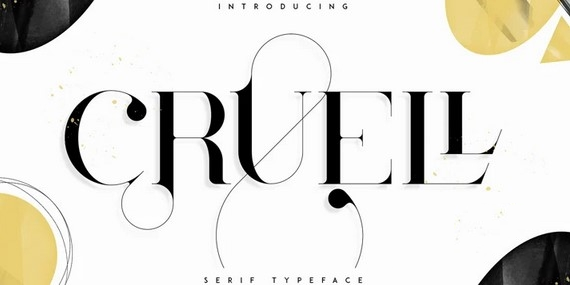
Представляем вашему вниманию шрифт Cruell Serif - 5 шрифтов
Cruell - это чистый, роскошный шрифт, состоящий из 5 шрифтов с глифами, альтернативами и многоязычной поддержкой, чтобы очаровать ваш следующий проект. Очень универсальный шрифт, который отлично работает в больших и малых размерах.
Cruell идеально подходит для брендинговых проектов, дизайна домашней утвари, упаковки товаров, заголовков журналов - или просто как стильное наложение текста на любое фоновое изображение.